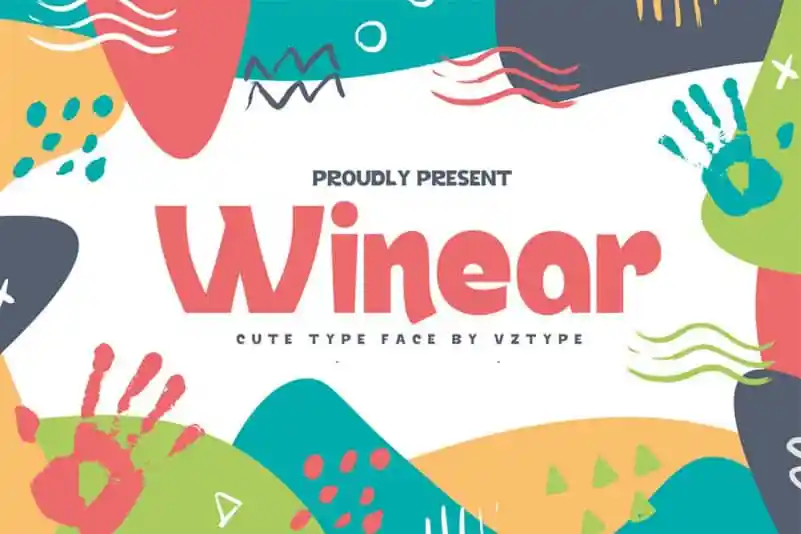
Winear Display Font – Download Grátis
Winear Display Font é uma tipografia de destaque inspirada nas divertidas revistas infantis dos anos 90. Esse design único foi criado pelo font designer Vztype, e seu estilo retrô garante um ar nostálgico que combina perfeitamente com o conceito atualizado de design moderno. Seu uso não só se adequa a ambientes vintage, mas também atende aos padrões contemporâneos dos designers gráficos, dando à sua arte uma sensação vibrante e inovadora. Além disso, Winear Display Font é altamente versátil e pode ser facilmente combinado com elementos visuais como ilustrações e fotografias. Esta característica torna-a perfeita para projetos que exigem um toque atraente e diferenciado em logotipos, identidades de marca, títulos e embalagens. Com Winear Display Font, você tem uma ferramenta poderosa no seu arsenal de design, que vai garantir que seus trabalhos se destacam entre os demais.